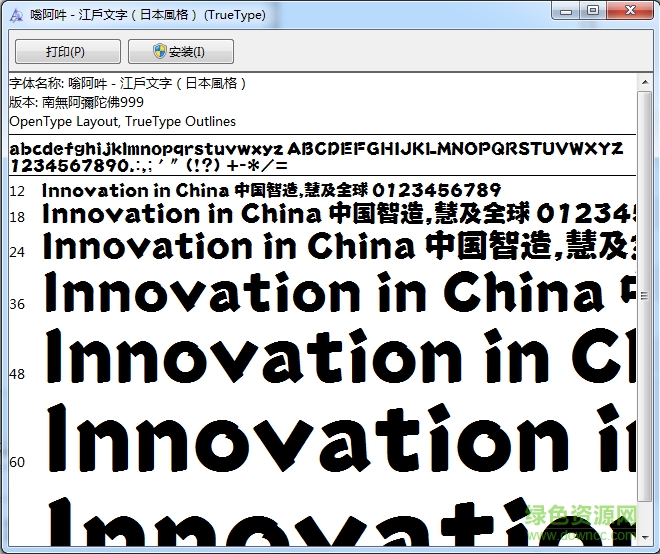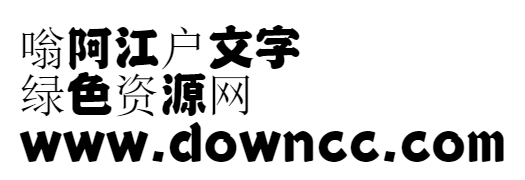
江戶文字字體
江戶文字是一款字跡深沉端正的日本字體,支持中文輸入,字跡在常規(guī)的基礎上有加黑和加粗的改變,給人印象深刻和極佳的辨識度,歡迎大家來綠色資源網免費嘗試!
江戶文字,全名嗡阿吽江戶文字,有著清幽干凈的日本風格,是由官方發(fā)行的、字庫較全的日本藝術字體,很有觀賞價值,可廣泛運用于平面設計、海報設計、廣告創(chuàng)意等領域!
日本江戶文字